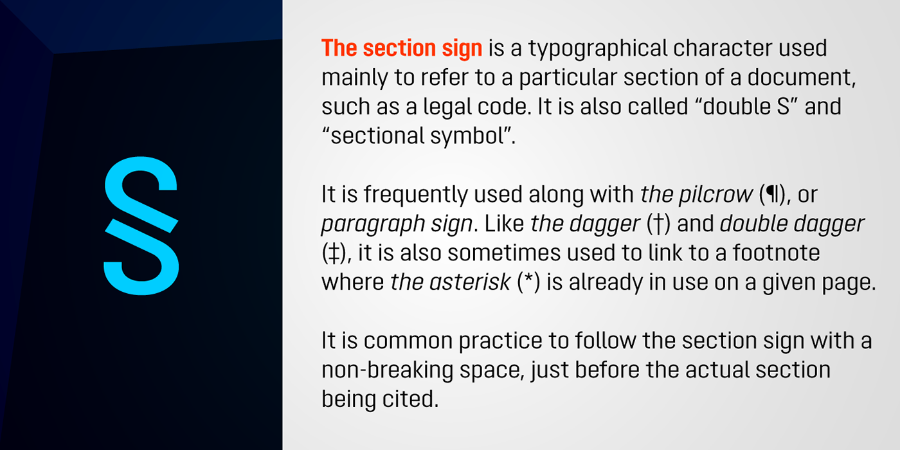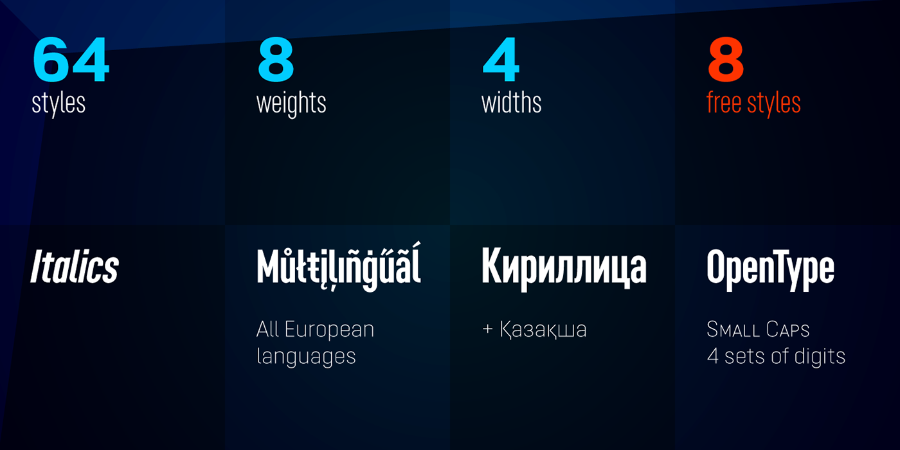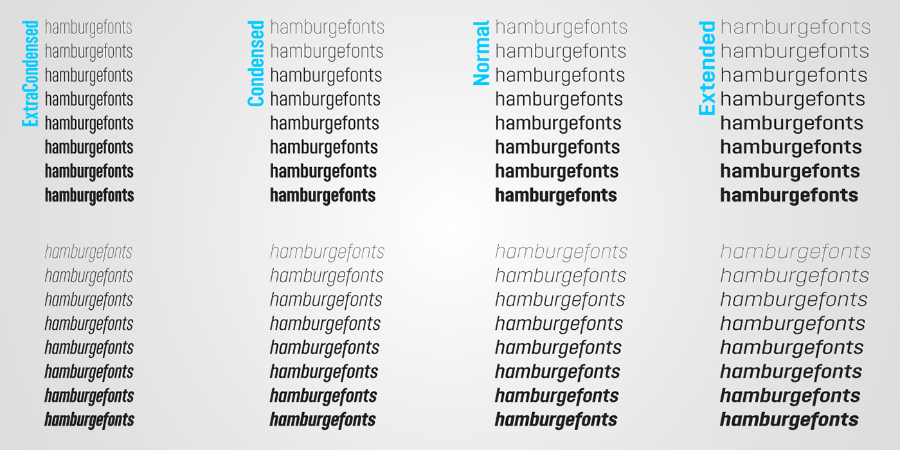
意见Pro字体免费演示
意见专业字体免费演示是一种几何怪异的无衬线字体与超大的x高度来64种风格。它由4个宽度变化组成,每个变量分别用8个重量和相应的斜体表示。它具有明显垂直杆的刚性曲线使其既可用于显示又可用于段落式字体。作为任何类型的寻路或标签等技术应用的字体,它也特别有效。在这里今天你可以有两个,意见额外浓缩光和斜体。